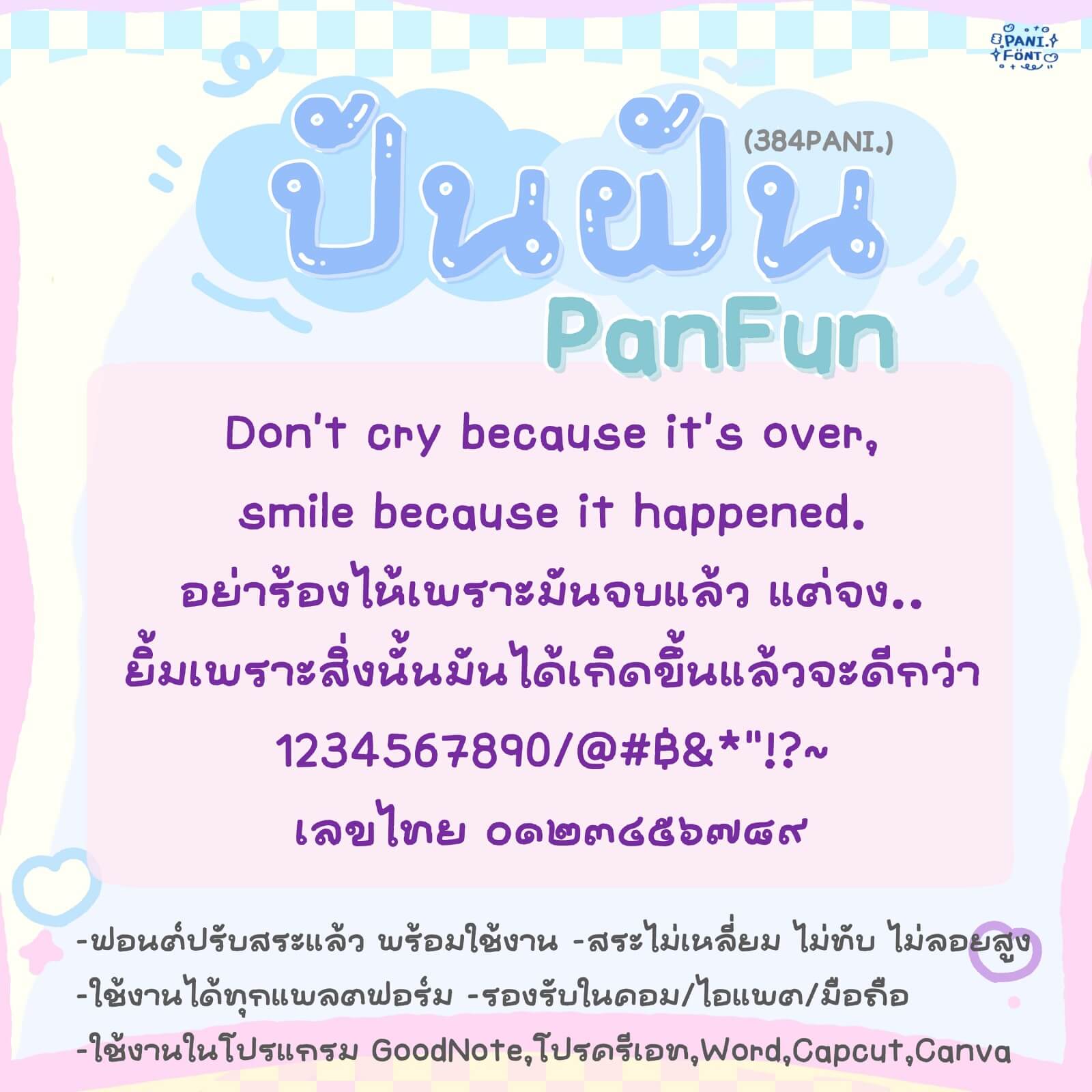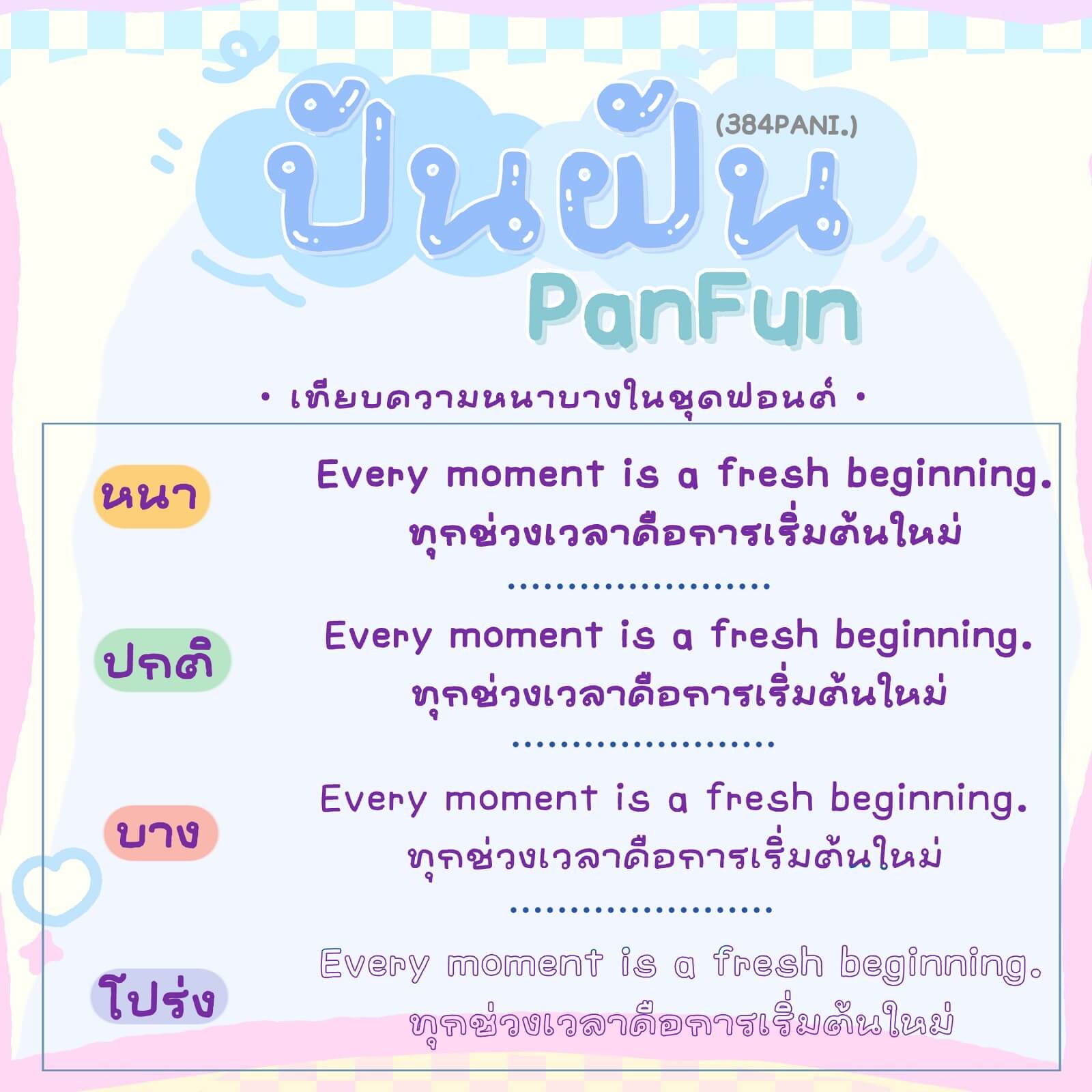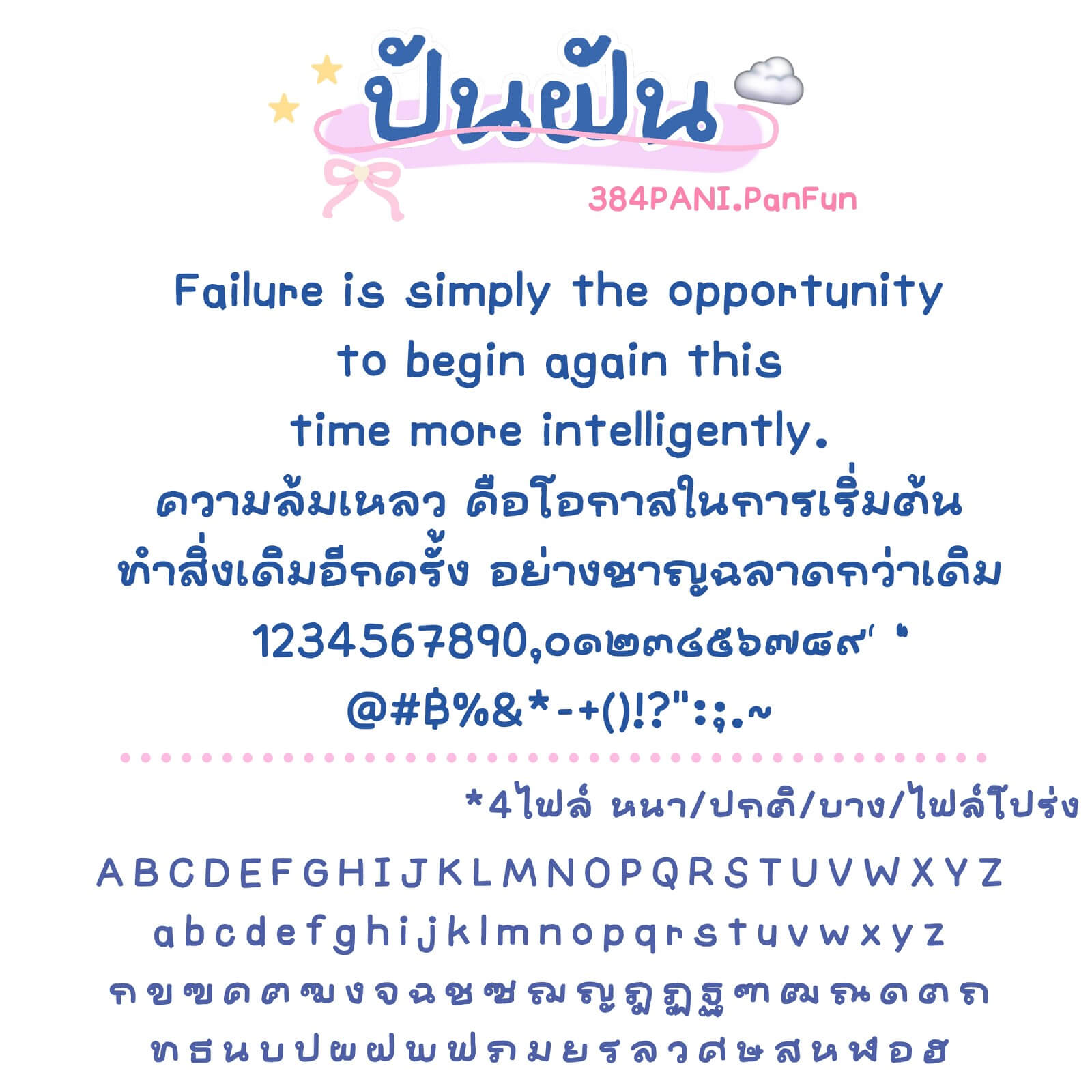
384PANI.ปันฝัน
ฟอนต์ 384PANI.ปันฝัน – ฟอนต์หัวกลม น่ารัก อ่านง่าย ใช้แต่งคลิป จดโน้ต ให้อารมณ์เข้าถึงง่าย
ฟอนต์มี 4 ไฟล์ – น้ำหนัก บาง ปกติ หนา ไฟล์โปร่ง